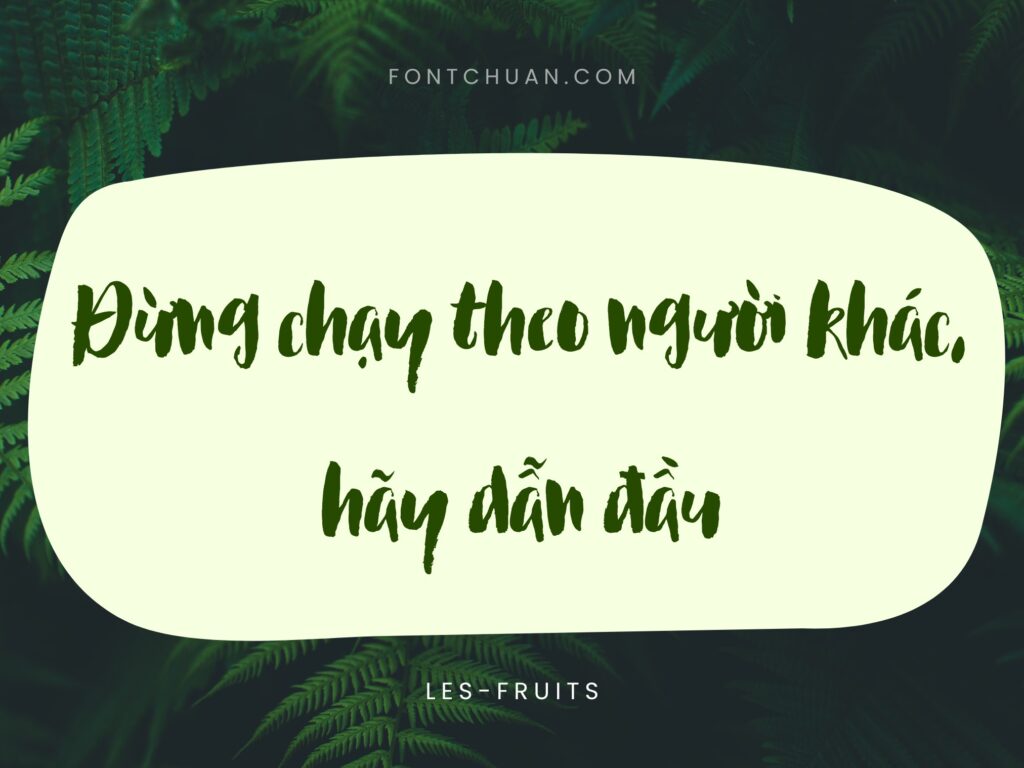
Font iCiel Les Fruits Việt Hóa
Les Fruits là một kiểu chữ viết tay nghệ thuật được thiết kế bởi Nicky Laatz, mang đến cảm giác tự nhiên và sáng tạo. Font này được tạo ra với các nét vẽ bằng cọ, phù hợp cho các thiết kế mang phong cách mực hoặc màu nước. Đặc biệt, Les Fruits đã được Việt hóa bởi Iciel, hỗ trợ tiếng Việt cùng nhiều ngôn ngữ khác, đáp ứng nhu cầu đa dạng của người dùng. Thành viên của Font Chuẩn đã sưu tầm và chia sẻ font này, giúp cộng đồng thiết kế ứng dụng dễ dàng trong các dự án của mình.
Về đặc điểm thiết kế, Les Fruits sở hữu các ký tự mềm mại, uyển chuyển, tạo nên sự thân thiện và gần gũi. Font này phù hợp cho các thiết kế như thiệp mời, logo, bao bì sản phẩm, poster và các ấn phẩm truyền thông xã hội. Ngoài ra, Les Fruits còn thích hợp cho các ngành nghề như quảng cáo, ẩm thực, thiệp cưới và spa, cùng các sự kiện đặc biệt như lễ hội, sinh nhật, Valentine và Trung thu.